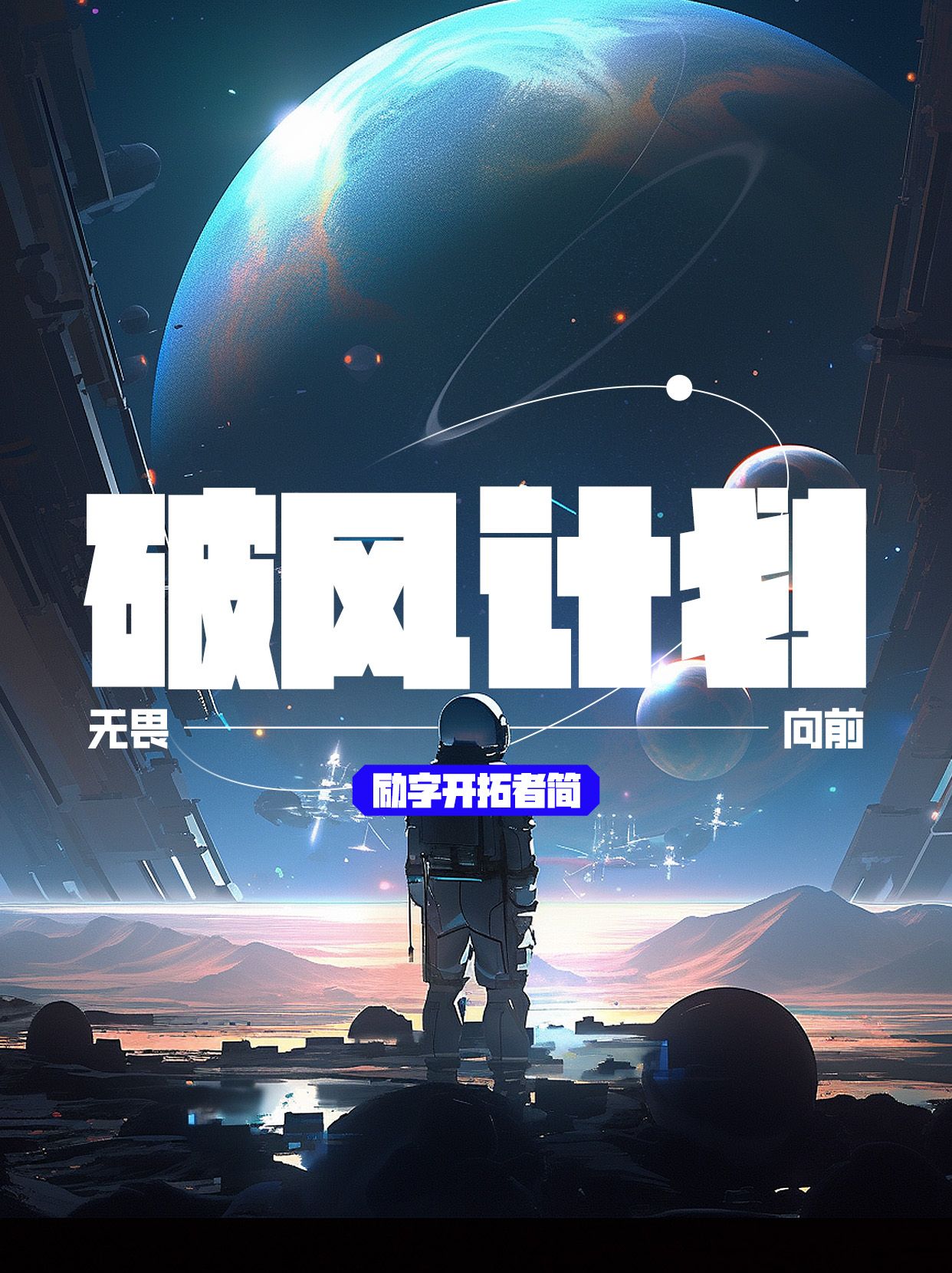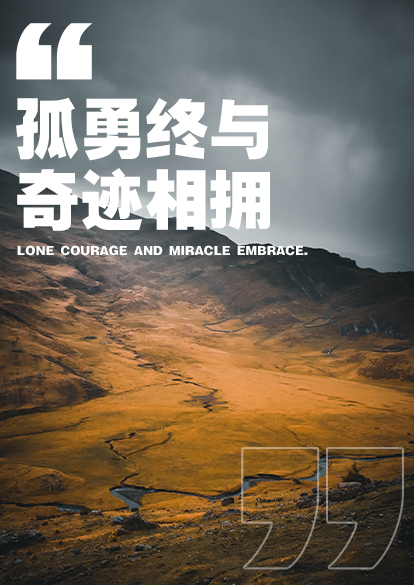
经典黑体字体的魅力与推荐
在字体设计的世界里,黑体字体以其独特的魅力和广泛的应用场景,一直受到设计师和用户的喜爱。今天,我们就来探讨一下经典黑体字体的魅力,并为大家推荐几款值得一用的黑体字体。
励字开拓者简 特级黑字形稳健,线条清晰,结构严谨,完美诠释了黑体字的庄重与力量。无论是应用于广告标题、品牌标识还是正式文档,励字开拓者简 特级黑都能展现出其独特的视觉效果和专业气质。其经典的设计,让文字瞬间成为焦点,是设计师们不可或缺的字体选择。
励字志向黑简 超粗,作为经典黑体字体中的佼佼者,以其独特的魅力赢得了广泛认可。其字形饱满,线条流畅,展现出力量与稳健的特质。无论是海报设计、品牌宣传还是正式文档,励字志向黑简 超粗都能以其独特的风格,赋予文字深刻的内涵和力量感。这款字体不仅具备黑体字的经典美感,更融入了现代设计的元素,成为设计师们钟爱的选择。
励字超级勇士简 常规,一款充满力量与动感的经典黑体字体。其字形设计独特,线条粗犷而不失细腻,彰显出强烈的视觉冲击力。无论是用于广告标题、海报设计还是品牌宣传,励字超级勇士简 常规都能轻松吸引目光,传递出坚定与勇敢的气息。这款字体不仅是设计师们的得力助手,更是展现个性与风格的绝佳选择。
励字超粗黑简繁其独特之处在于超粗的线条设计,不仅彰显了字体的力量感,更增添了视觉上的冲击力。无论是繁体还是简体,都能在这款字体中找到独特的韵味。它适用于各种需要强调和突出文本的场合,如海报、广告、标题等。选择励字超粗黑简繁,让您的文字瞬间脱颖而出,成为焦点。
经典黑体字体以其独特的魅力和广泛的应用场景,成为了字体设计领域的一颗璀璨明珠。无论是设计师还是普通用户,都可以根据自己的需求选择合适的黑体字体,为作品增添一份独特的韵味。